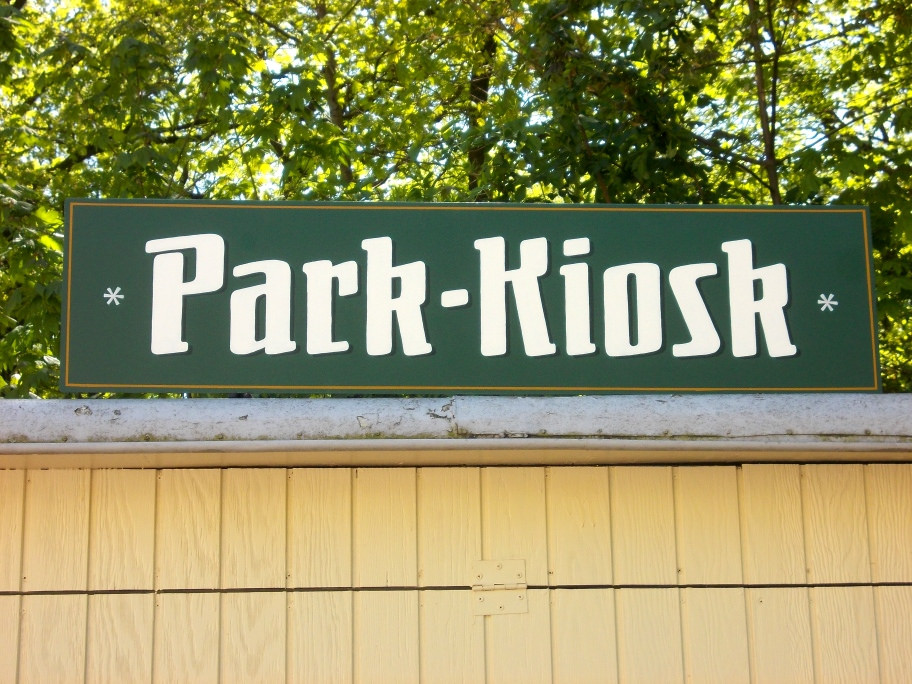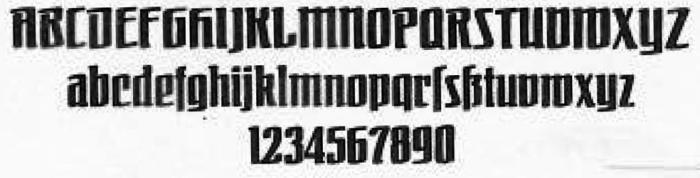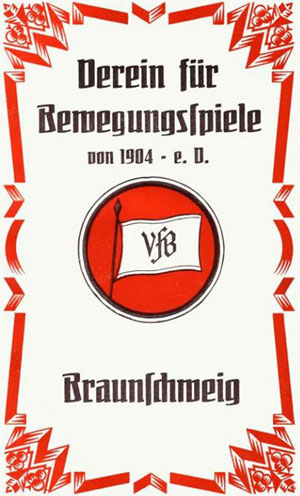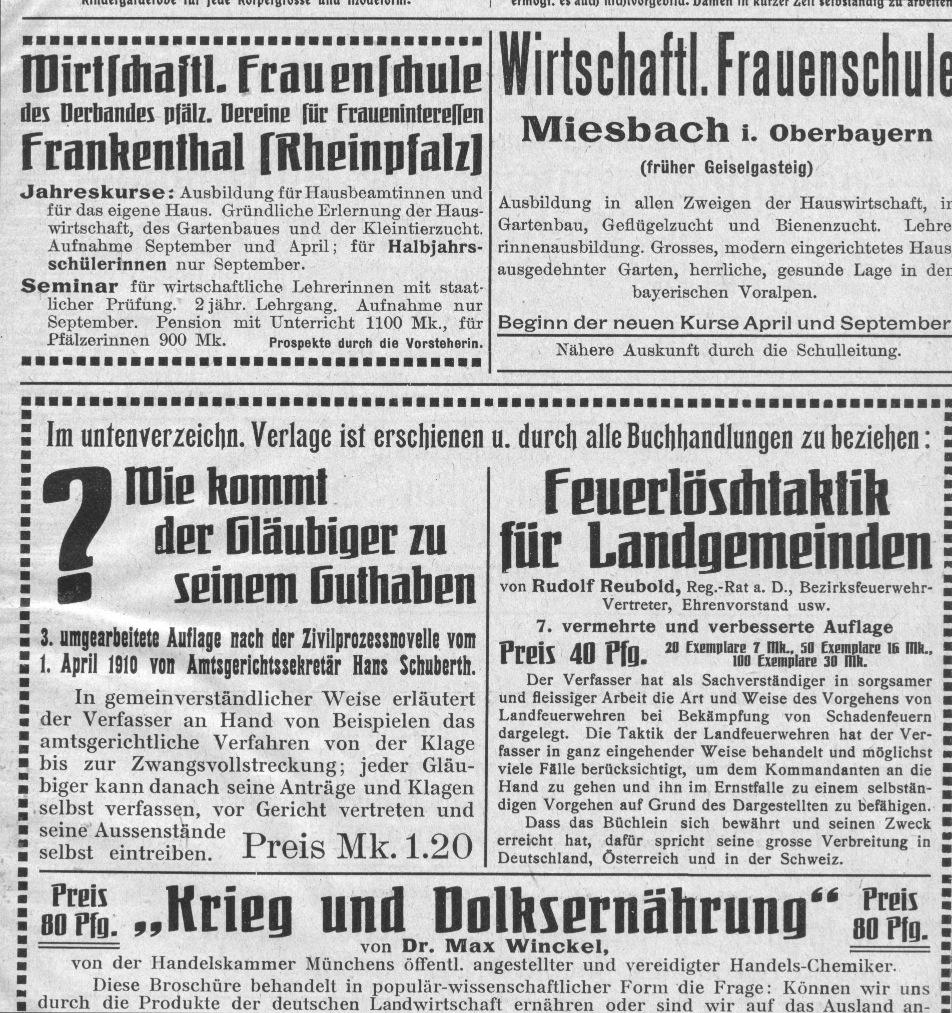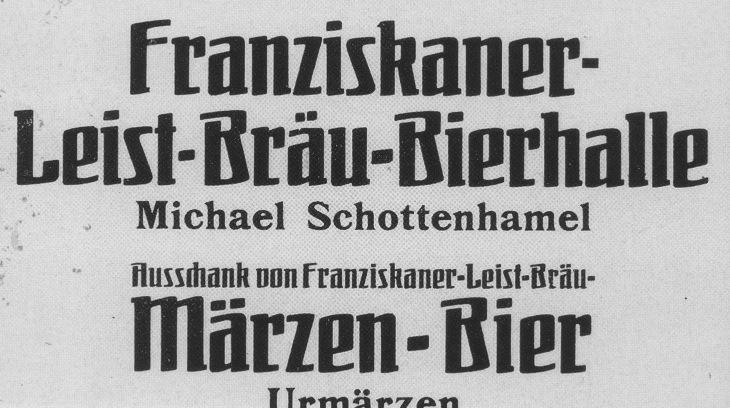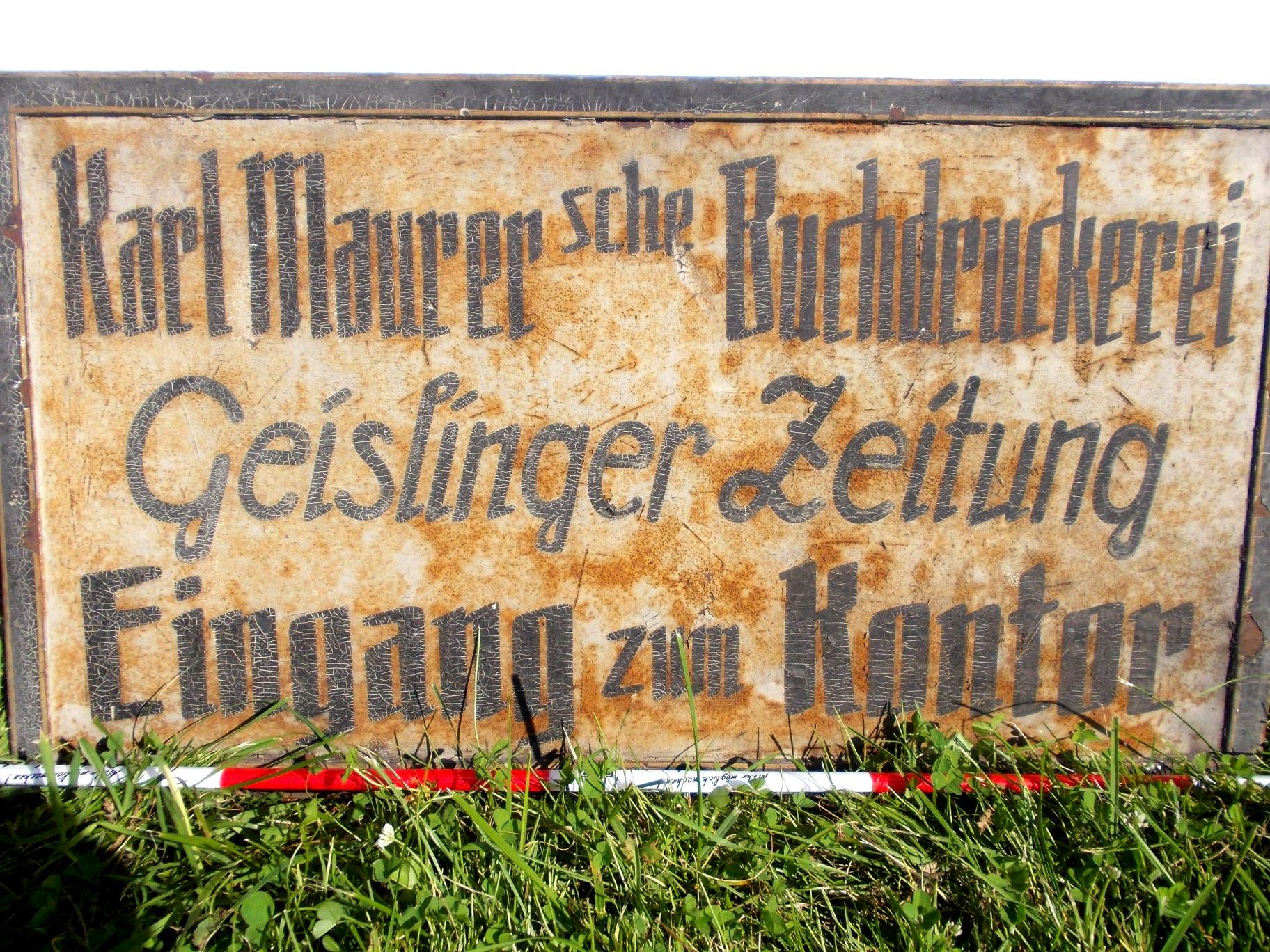
Schriftmuster gesucht
Ein Kollege ist gerade dabei, die Schrift »Bombe«
(Otto Ludwig Nägele, Ludwig & Mayer, Frankfurt am Main, 1908)
zu rekonstruieren.  Leider konnte ich ihm nur ein unvollständiges
Schriftmuster (Anhang) anbieten. Hat jemand ein komplettes
Figurenverzeichnis und kann dies hier einstellen?
Die Schrift »Engel« ist im Original zwar auch von Nägele,
basiert aber auf seiner »Feder-Antiqua« von 1911.
Bei Google Fonts gibt es eine Version der »Feder-Antiqua«
unter dem Namen »Federant«.
Diese Angabe stammt offensichtlich aus dem Internationalen Index der Bleisatzschriften
vom Kollegen Hans Reichardt. Eine Schriftprobe der Kometa fehlt im Index allerdings
ebenso  wie die Angabe einer Gießerei — und einen Entwerfer O.E. Lehmann sucht man
sogar in der Künstler-Liste des Klingspor-Museums vergeblich...
Über die Gießerei Osip Lehmann habe ich im Netz folgenden historischen
Text gefunden:
„Eine der bedeutendsten und, was Selbstständigkeit anbelangt, wohl die bedeutendste
Schriftgiesserei Russlands i
st die im Jahre 1854 gegründete von Osip Lehmann in
St. Petersburg. Diese Giesserei, die heute einen Umsatz von  ca. 50.000 Rb. erzielt,
hat sich vorzugsweise auf die Herstellung russischer und überhaupt slavischer Schriften
gelegt und besitzt vielleicht eine der vollständigsten Sammlungen derselben .
In der Werkstätte befinden sich gegen 25.000 aus derselben hervorgegangene
Stahlstempel (Patrizen), die ihrer Hauptzahl nach slavischen Schriften
angehören. Auch im Gusse kleiner Nonpareilleschriften und in dem von Vignetten, Rand-­ und
anderen Verzierungen weist die Lehmannsche Schriftgiesserei hervorragende Leistungen auf
und exportirt sogar Matrizen nach dem Auslande. Die Giesserei produzirt jährlich 4000 Pud
verschiedene Schriften und stehen bei ihr 16 Gussmaschinen (12 für kleinere  und  4 für grosse
Schriften) und 5 eiserne Oefen in Verwendung;  ebenso  befindet  sich bei der Lebmannscben
Giesserei,
welche 3 Meister, 35 Gehülfen  und 12 Lehrlinge beschäftigt, eine
mechnische Werkstätte für Reparatur von Gussmaschinen etc.  Diese
Giesserei
wurde  mit   sehr  geringen  Mitteln  und  in  ganz  kleinem Maassstabe gegründet und hat sich
aus sich selbst zu dem herausgearbeitet
, was  sie ist.“
Ich habe ein paar Vorlagen für die Bombe gefunden. Habe damit auch schon Beschriftungen gemacht.
Park-Kiosk
magst du uns evtl. etwas mehr über den auftrag erzählen, wie bist du auf die 'bombe' gekommen, woher stammt dein foto und hast du die schrift extra dafür nachgezeichnet?
@RobertMichael  Hallo Robert, danke für den Hinweis auf Boernie und seine vau-ef-be-Seite. Ich wusste nicht, dass Boernie Bernhard Schnelle ist. Ich beschäftige mich schon lange mit dieser Schrift und ihren Varianten weil ich als Schriftenmaler sehr viel für die Augustiner Brauerei in München arbeite. Die Hausschrift von Augustiner, ist der "Bombe" sehr ähnlich. Sie basiert wahrscheinlich auf der "Enge Münchener Fraktur"  von Flinsch/ bzw. der Bauerschen Gießerei. Mein ehemaliger Chef von der Schriftenmalerei Triebenbacher, die es bis vor ein paar Jahren in München noch gab, hat von den 1950ern bis in die 90er Jahre fast alle Fassaden- und Schilderbeschriftungen für Augustiner gemacht und diese Schrift dabei immer wieder variiert. Ich bin nun dabei sie in mehreren Schnitten zu vereinheitlichen und zu digigitalisieren, was sehr aufwendig ist. Ich nehme eine große Sammlung an Fotos von diesen Beschriftungen dafür als Grundlage. Mehr Beispiele dieser Schrift in gemalter Form hier: